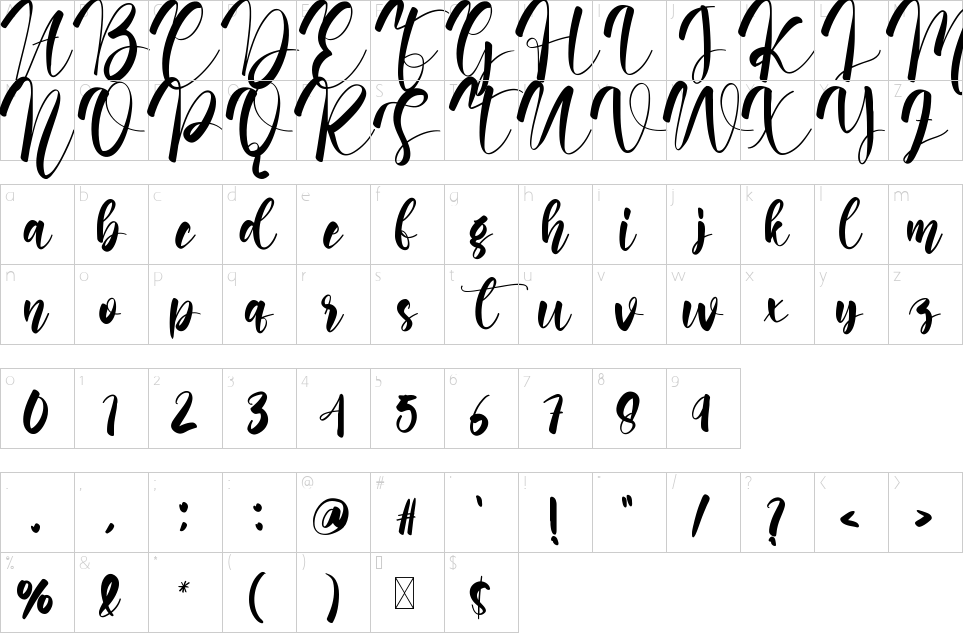
Downright Font – Fonte Grátis
Downright Font
Descubra Downright, uma nova fonte gratuita que adicionará uma aparição fresca ao seu design visual. Desenvolvida por scratchones, esta elegante e funcional fonte foi projetada para oferecer um toque único em qualquer projeto editorial ou personalizado. Com seus detalhes sutilmente bem definidos e sua disposição agradável, Downright não apenas facilitará o processo de edição do texto, mas também adicionará uma capa visual profissional. Se você está procurando por uma fonte que ofereça tanto estilo quanto facilidade, Downright é uma escolha ideal para incorporar em seu portfólio digital. Até agora, Downright foi baixada 886 vezes e continua a ganhar adeptos cada vez mais.
Mapa de caracteres da fonte Downright Font